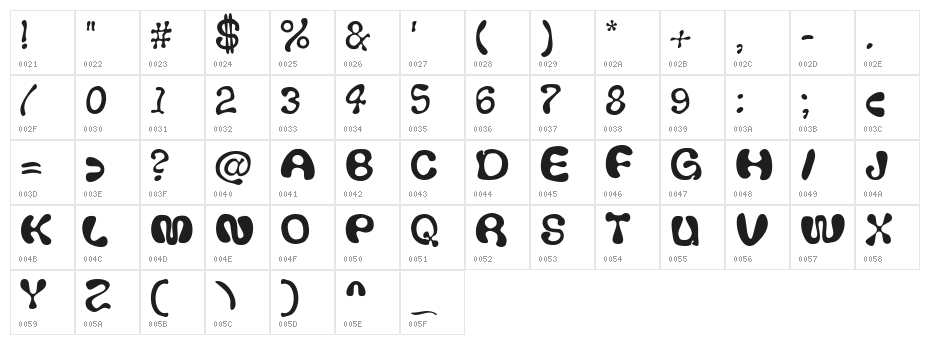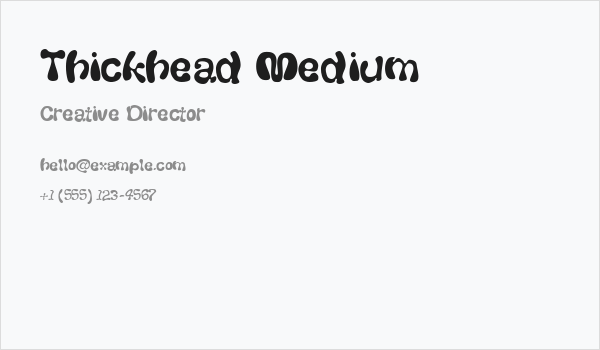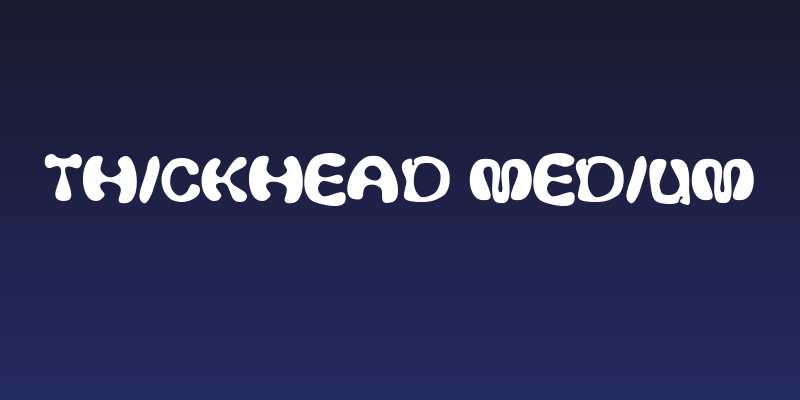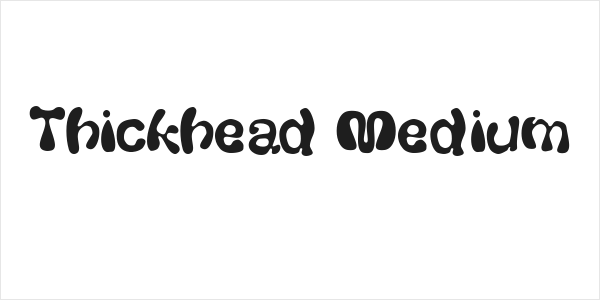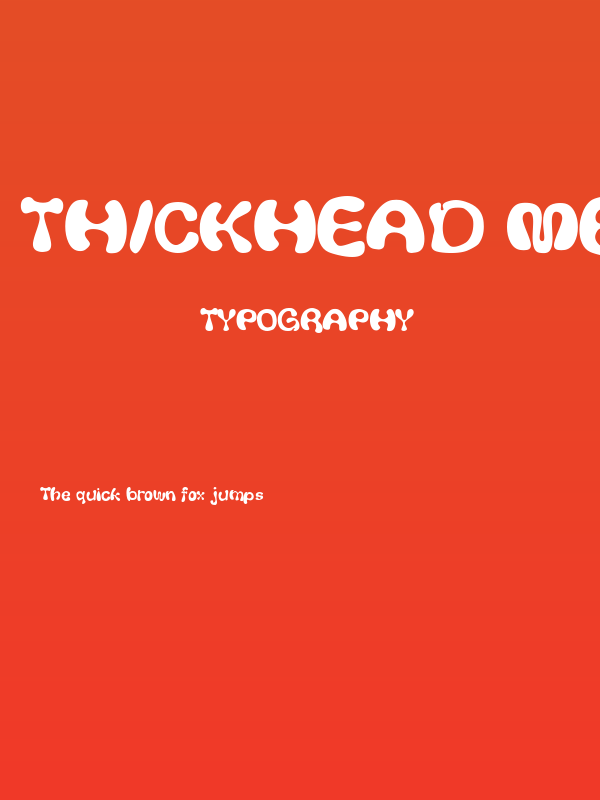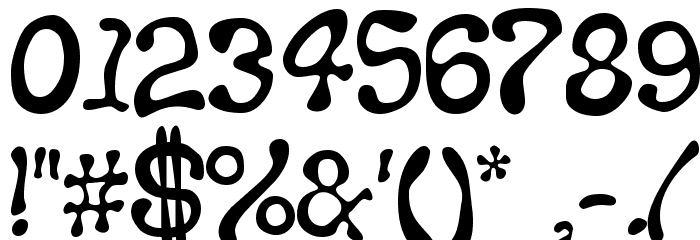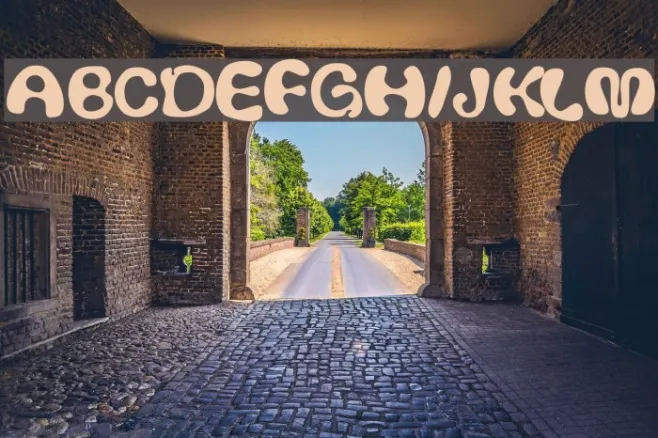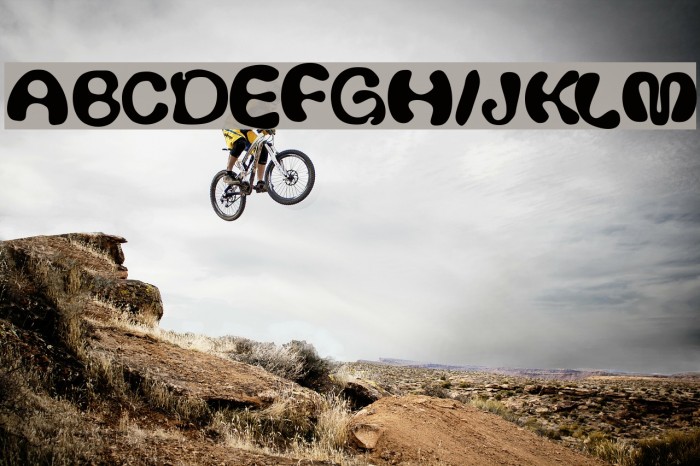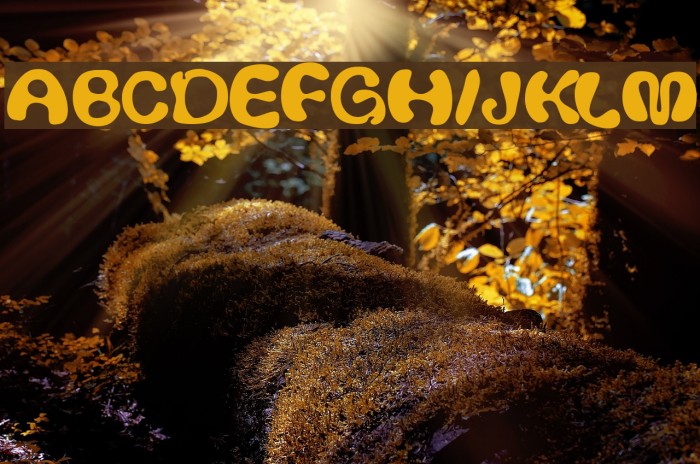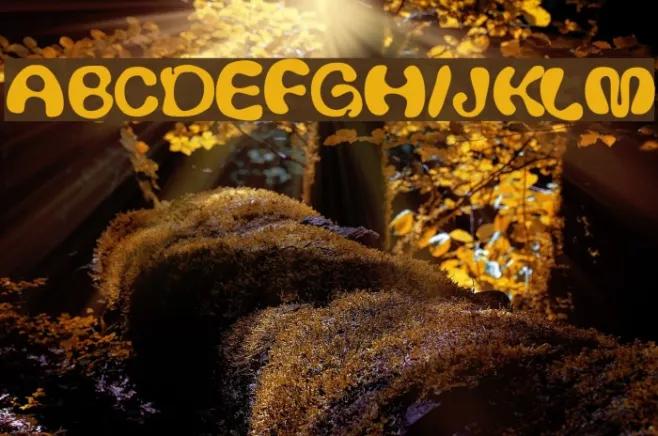
Thickhead Medium Font
| Stile generale | Playful, Whimsical |
| Progetti proposti | Ideal for children's books, playful branding, posters, and creative projects that require a fun and informal touch. |